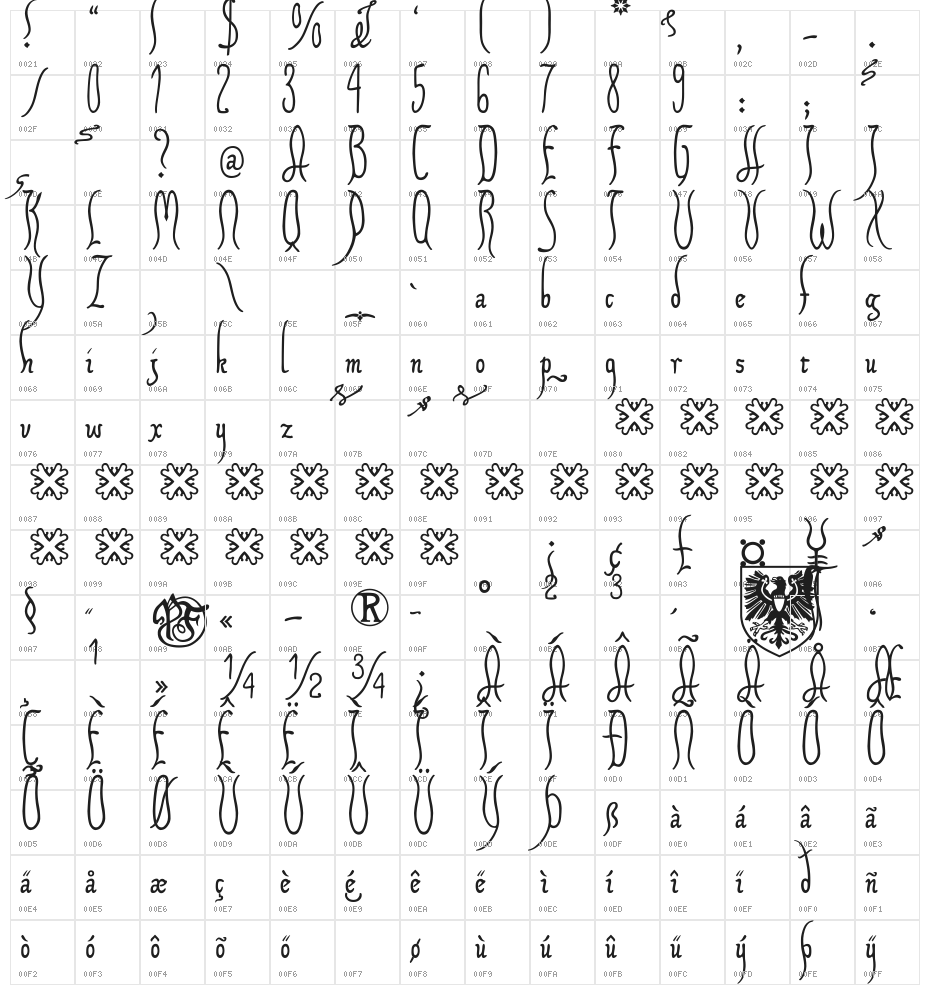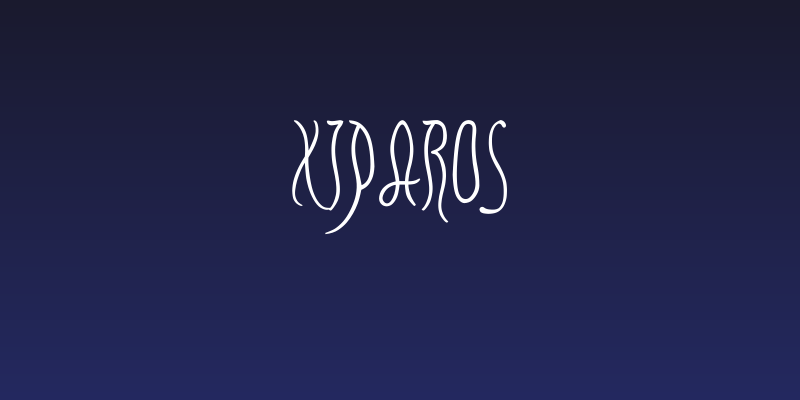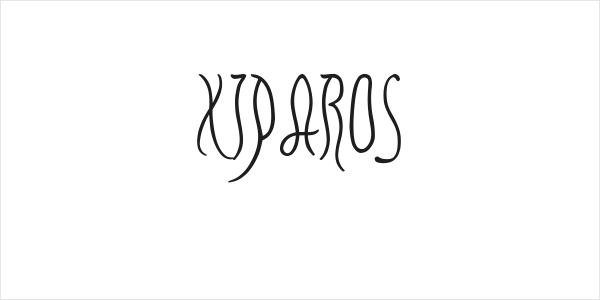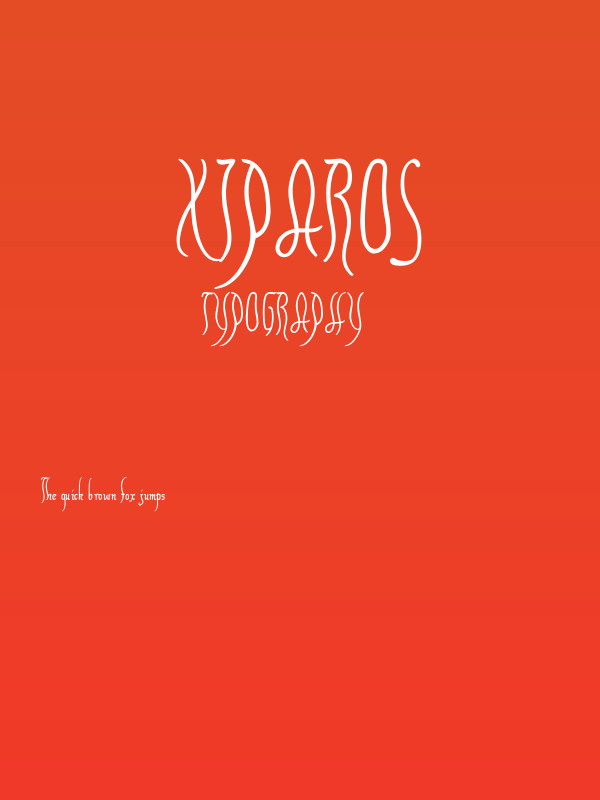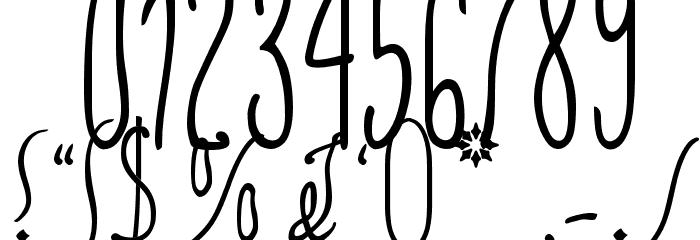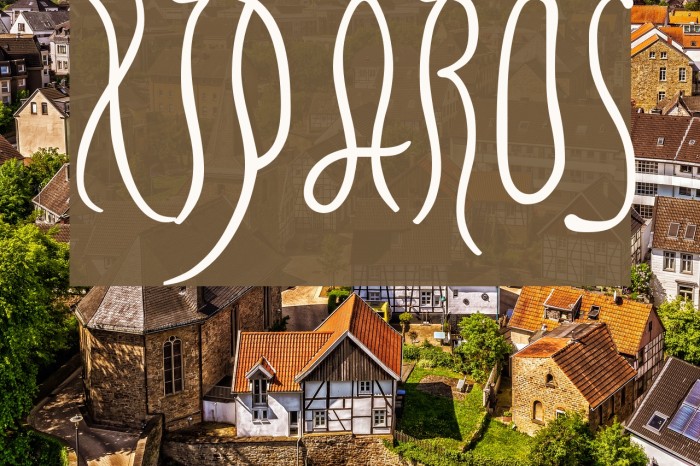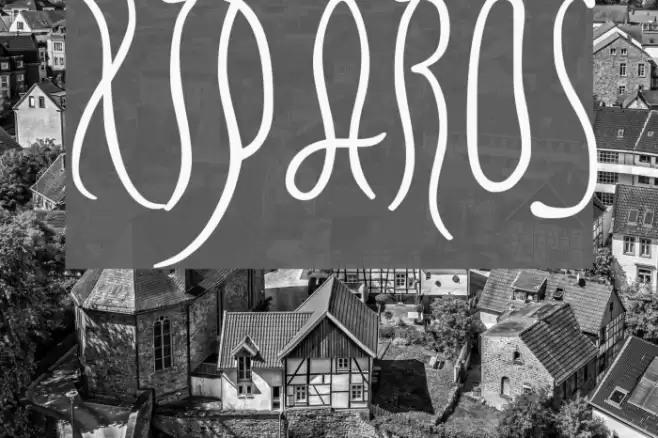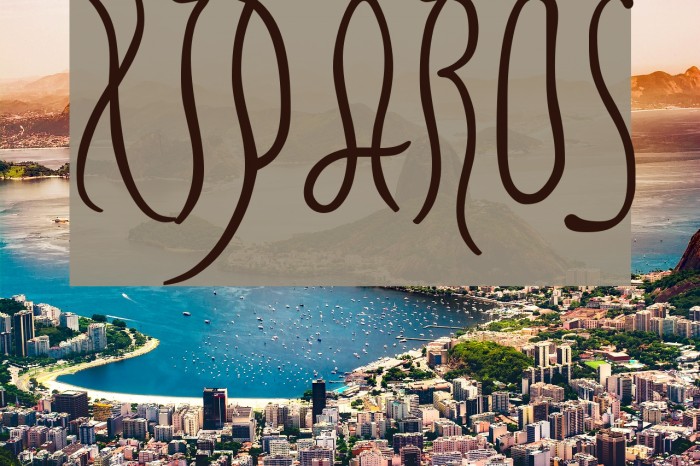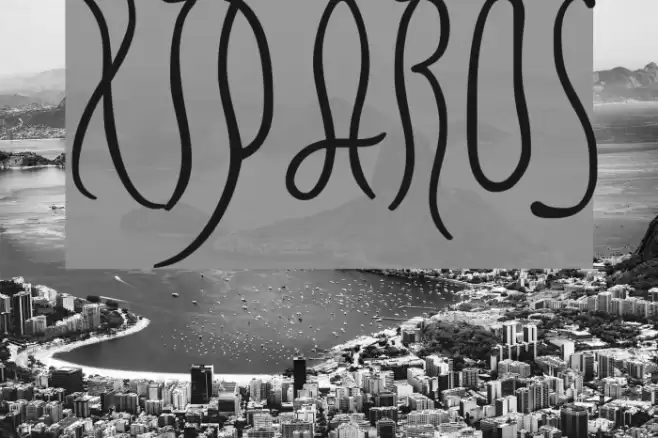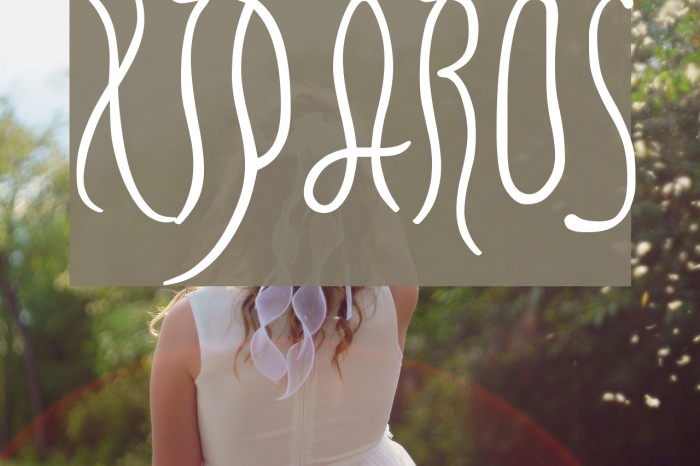
XIPAROS Font
✎ Gothic
| カテゴリ | Gothic |
| 用途 | Logos, Headlines, Artistic projects |
| おすすめプロジェクト | Ideal for creative projects such as invitations, posters, and branding materials that require a distinctive and artistic touch. |